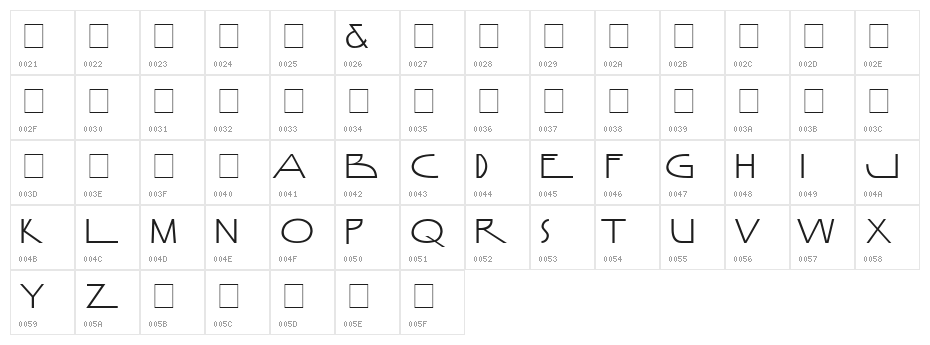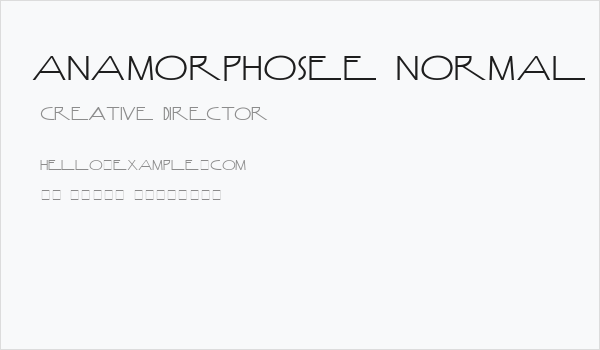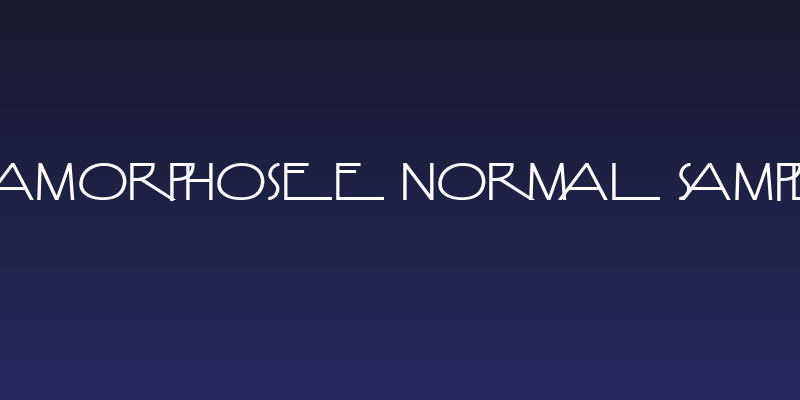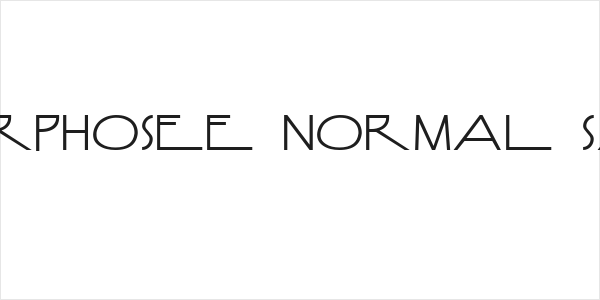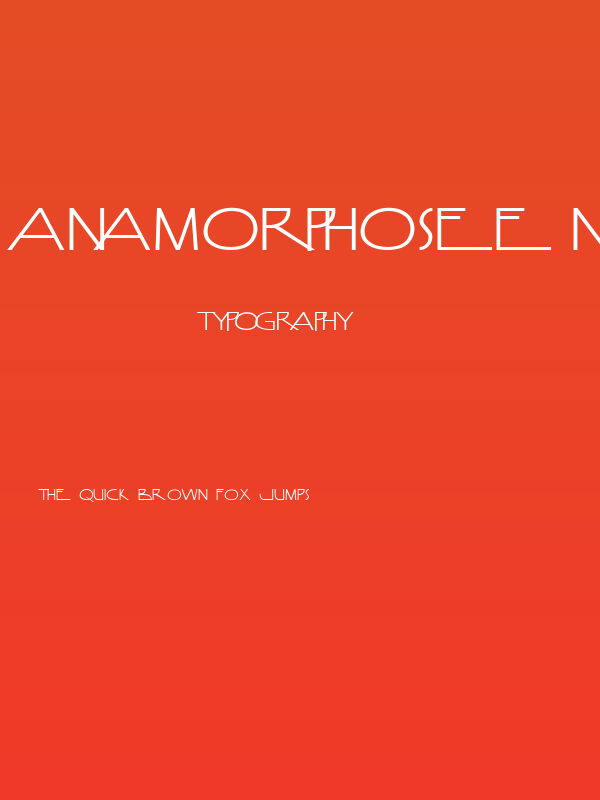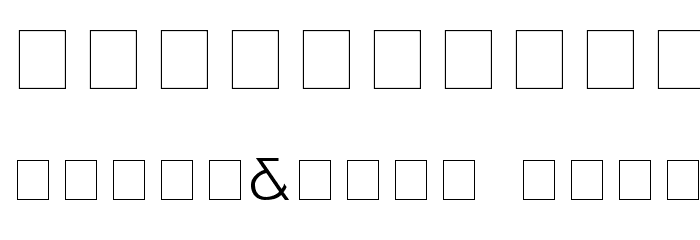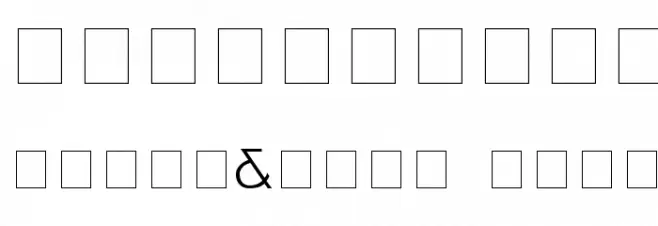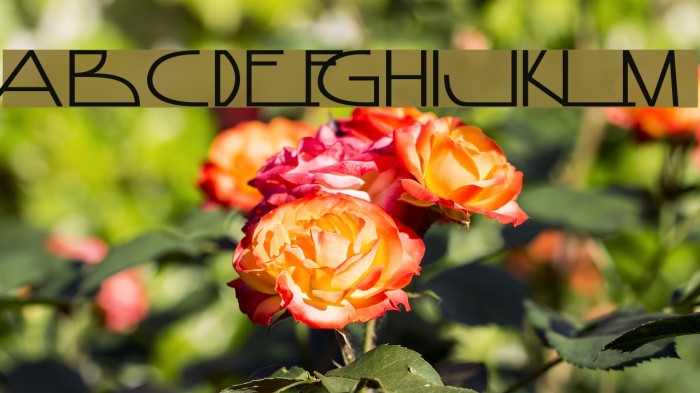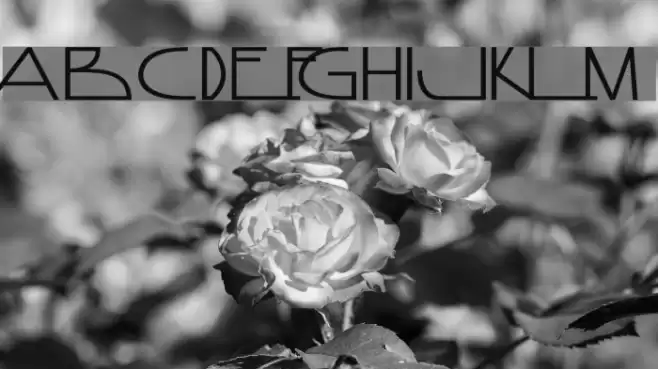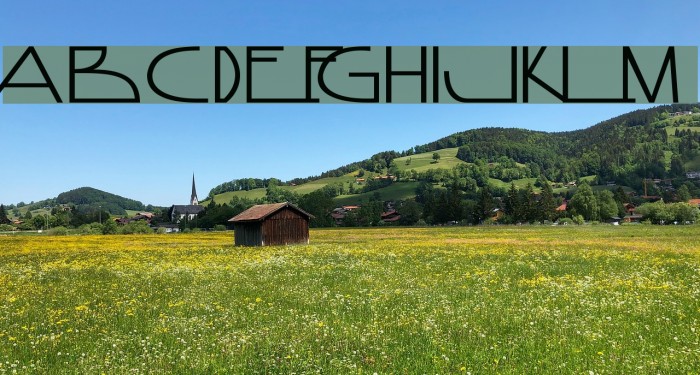
Anamorphosée Normal Sample Font
| Caso de uso | Headlines, Logos, Digital media |
| Proyectos propuestos | Ideal for branding, advertising, and digital media projects that require a contemporary and innovative look. |